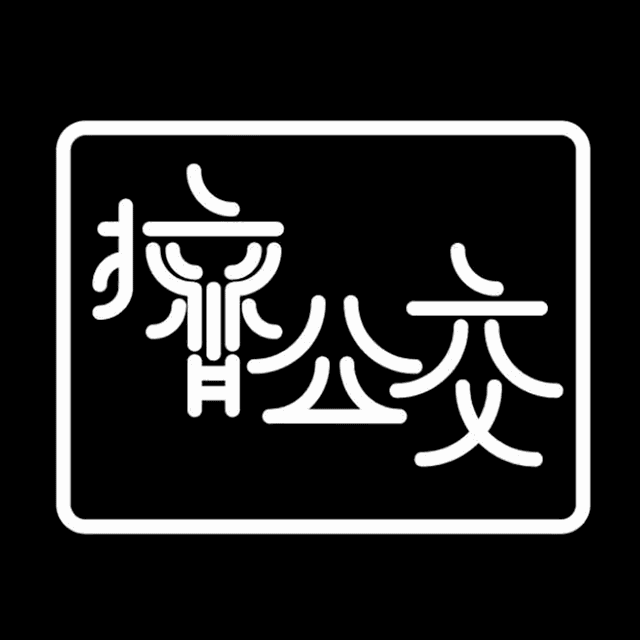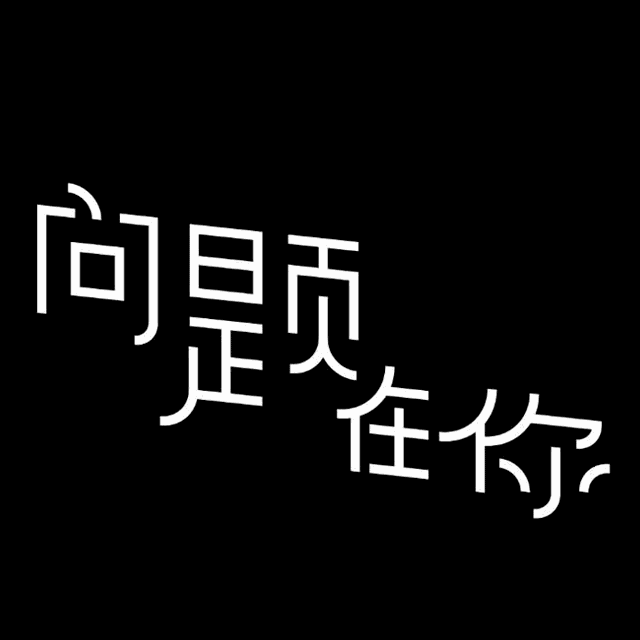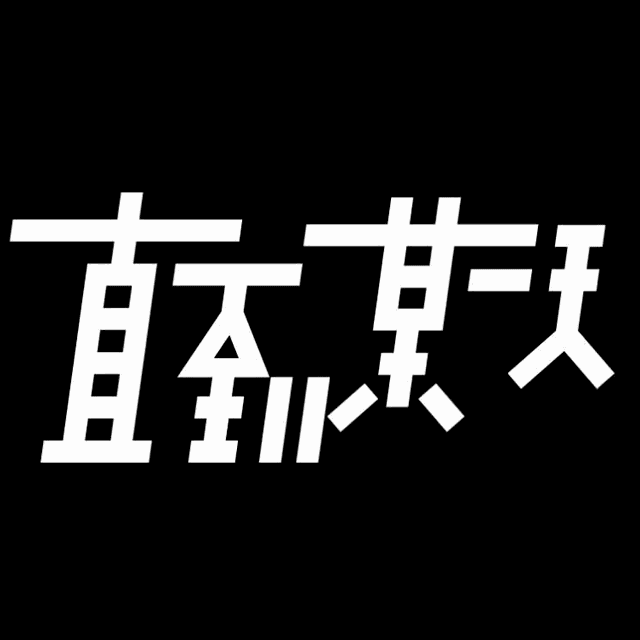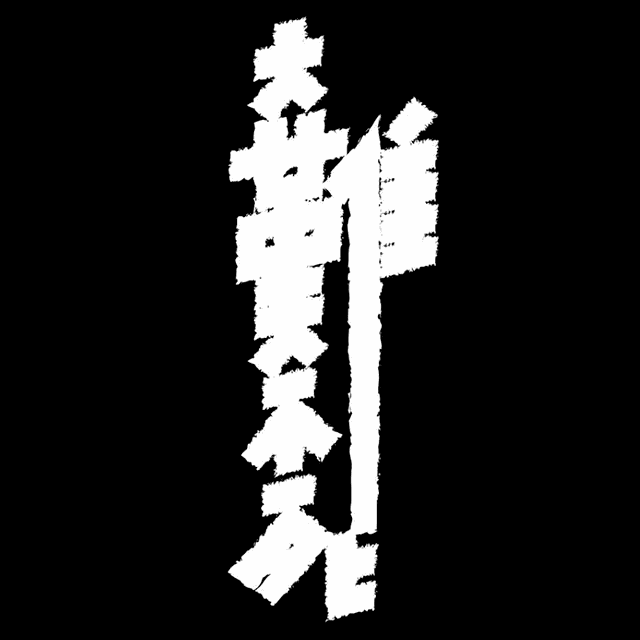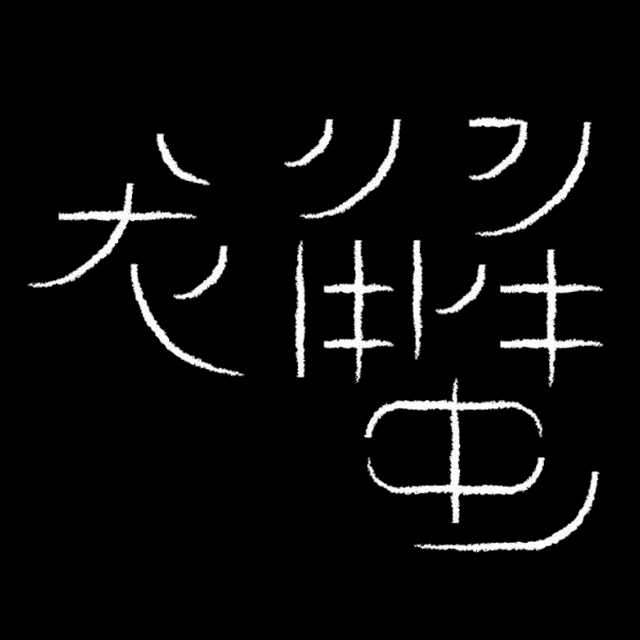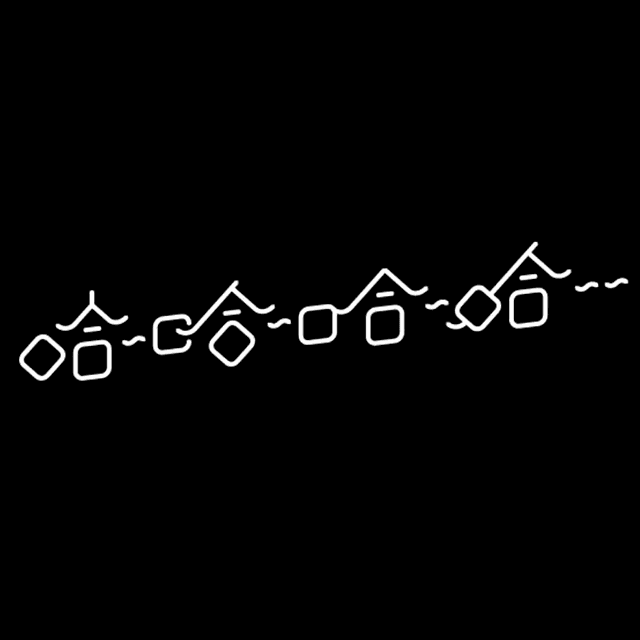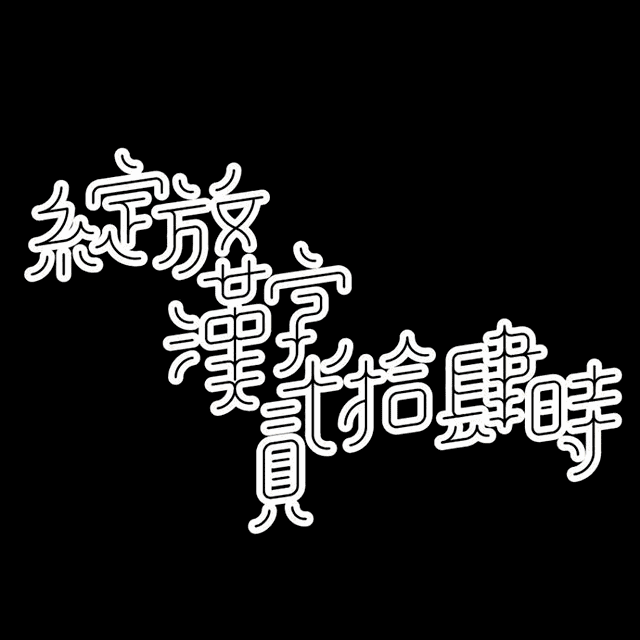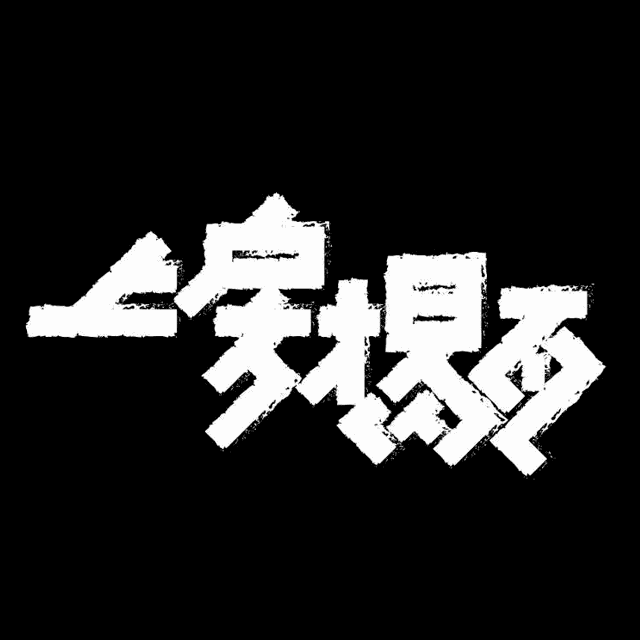
设计师印象 | 岳昕:字体设计魔术师
文/「字在」品牌创始人刘美松
恕我孤陋寡闻,在字体设计领域,我并不认识什么人。大约在2014年,李佛君说字组有个活动,要去上海参观上海字模一厂,我作为“卧底”,参与了这次行动。当时他推崇备至的是杭州的一个字体设计师张弥迪,说是如何如何的了得,我不是行内人,对于这个“了得”就有些茫然。
当年深圳有一个展览,刚好在网上查到了弥迪的作品,便通过佛君联系到他,没想到弥迪也是非常爽快的人,一下子答应下来。后来专门去过一次杭州拜访,碰巧还遇见了蒙纳字库前去的朋友,不单是对弥迪的了得有所见识,对字体设计的认知,又增进了一点点。
△岳昕老师
第一次认识岳昕老师,是在北京某酒店的一个大堂咖啡厅,通过汉仪字库的首席运营官马忆原介绍。大多的细节也忘记了,只记得他说话的声音极小,也慢,谦和的人大概都这个样子吧。
△岳昕老师作品欣赏——动作词组1
△岳昕老师作品欣赏——动作词组2
见面跟岳昕老师汇报了一下「字在」当下所做的事情,说了什么也不记得了,因为「字在」一直在发展,也一直在调整、在变,虽然后面没有什么质的合作,但怎么也混了个脸熟,承蒙岳昕老师不弃,这朋友算是交上了。
△岳昕老师作品欣赏——热词1
△岳昕老师作品欣赏——热词2
再见岳昕老师,是在深圳。当时是汉仪在深圳大学做了一个字体设计课程,深圳诸多的字体设计精英悉数到场,当然也有李佛君,还有张昊、顾正友等等,这个时候,我由当时的菜鸟,变成在字体设计圈能混得个脸儿熟了。也就是在这个课程的现场,看到了岳昕老师粉丝的影响力,以至于后来,我也成了“昕”粉中的“新”粉。每每想到这种结缘,真的有时候就让人莫名的感动。
△岳昕老师设计,「字在」之幸
和岳昕老师什么时候加的微信又不记得了,2016年底的某月某日,闯入到岳昕老师的微信个人空间,惊讶发现他几乎是天天在设计,天天在发朋友圈。开始是局部跟踪,后来是全面进攻,继而是全面拷贝下来,这样由惊讶变成惊喜,又从惊喜变成了崇拜,一路跟来,一路享用这汉字字体设计的盛宴。为了不独享其美,我开始慢慢编辑,慢慢转发。美,一定是大家的,大众的,作为一个简单的搭桥者,心中亦是无限美好。
△岳昕老师作品欣赏——两字词组
△岳昕老师作品欣赏——三字词组
△岳昕老师作品欣赏——四字词组1
△岳昕老师作品欣赏——四字词组2
从来没有问过岳昕老师贵庚几何,首先在我面前是长者,是老师。但在岳昕老师的设计中几乎见不到丝毫“匠”气以及年龄段印记,全然的自如、朴拙,轻松、幽默且灵动,这一切,还原成一个词的话,就是“舒服”!在这个急吼吼的时代,能放下欲求,只为热爱而生活的人可以说是凤毛鳞角了吧。
△岳昕老师作品欣赏——短句1
△岳昕老师作品欣赏——短句2
每天和岳昕老师的作品不期而遇,真的感动于他无限的创造力。觉得他不只是一个设计师,而是一个诗人,无限的灵感扑捉,让文字以舞蹈的姿态,跳着、蹦着、走着来到我们的面前,走近了,又像是我们的某个亲人,日常生活中的某个朋友,有时候,还像是村里某个调皮的孩子,吐个舌头,抛个媚眼,跑开去!
△岳昕老师作品欣赏——竖排文字
设计上的专业,我的一通胡说八道,可能会贻笑大方。但在与岳昕老师相处的过程中,他全方位的谦逊态度,总是让人如沐春风。
第三次见面,是得知岳昕老师在汕头大学上课,通过吴勇老师的邀请,这次不单是让岳昕老师有了深圳之行,而且还见到了岳昕老师的夫人卢老师。卢老师可谓是快人快语,用她的话说是自来熟,因为卢老师,我也就能挖到一些岳昕老师设计之外的生活料道。
△岳昕老师作品欣赏——饮食相关词组
在北京,岳昕老师的上班方式是步行,单程50分钟,一天是100分钟。我问岳昕老师,要是下雨呢?他说北京的雨都不大,打伞就可以了。就这样风雨兼程且云淡风轻,还持之以恒,这是工作之外的智慧。通过这样的步行,不单是身体好了,而且体重也下降了10多斤。这一切,都是健康心态的呈现。
△岳昕老师作品欣赏——语气词组
可以说,我在和岳昕老师不长的交往过程中,看到了两个坚持:坚持设计和坚持走路。一个是爱,另一个还是爱,一个是对美和创造的爱,一个是对生命、身体和家的爱。我们只有对自己有爱,才可能对别人以及事物有爱。但愿我自己也能从中能悟出一点什么?
△岳昕老师作品欣赏——正能量词组
再看看我从网上找到的一些岳昕老师的介绍——2008年北京奥运会官方海报设计八人小组成员,汉仪首届“字体之星”字体设计大赛一等奖获奖作者,中国移动VI设计及营销渠道的形象整合,中国南方航空公司VI设计及整合,国家图书馆VI设计及整合,首都博物馆VI设计,《瑞丽》集团形象设计等等。
但是和岳昕老师的相处中,从没有提到过一丝一毫的荣誉。也许真的有这种淡然之心的人,才把自己放得那么那么的小,而这种小,不正是我们这个喧嚣时代无限稀缺的珍宝吗?
△【岳昕老师设计欣赏】:岳昕老师(中)来深,携夫人同行(照相者),不二空间,有【铁粉】三、五,夕阳中【不忍直视】,【隔壁老王】江涛(左一),依然坚持。杰哥(左二)讲茶、倒茶,【不得不说】这些许时光【金(也)不换】,吴勇老师(右二)在侧,【快快围观】,也不至于【看一次笑一次】,各位看官,【后果严重】至此,还不快快点赞,更待何时!